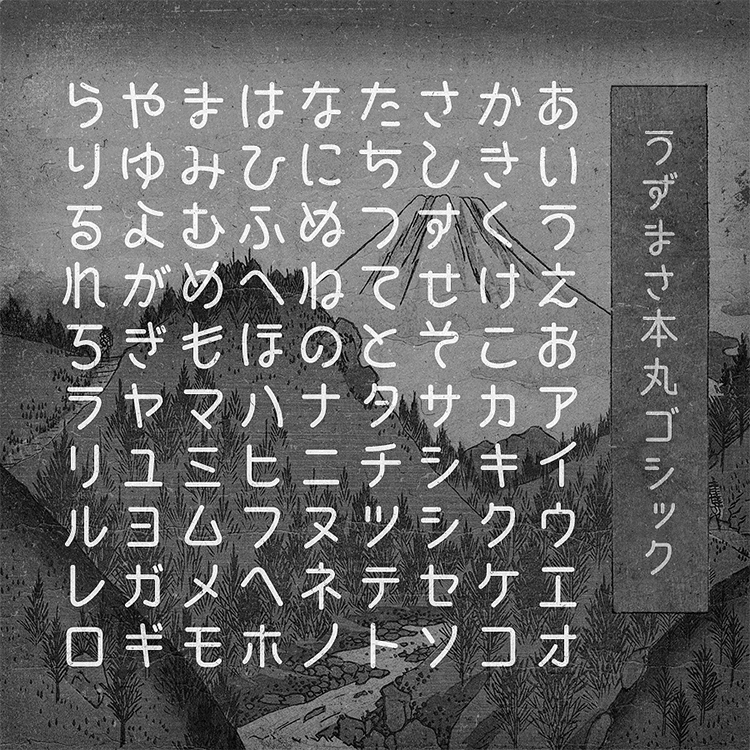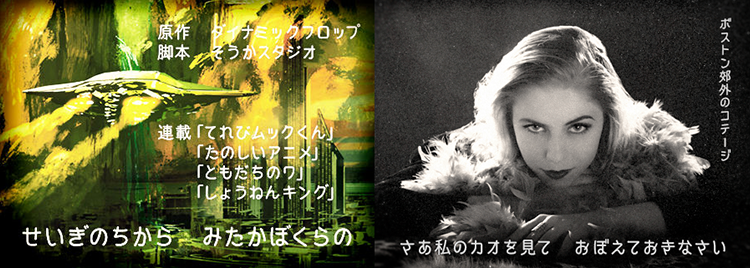
うずまさ本丸ゴシックは、無声映画時代(戦前1920年代)の字幕文字をヒントに、現代に蘇らせたフォントです。京都市右京区太秦(うずまさ)をイメージした、丸ゴシック体のフォントになっています。暖かみのある字体が特徴で、YouTubeやニコニコ動画などの字幕から、ロゴや雑誌などの紙媒体まで幅広く使うことができます。
字体は規則性があり、モダンな印象を与えます。和風なデザインから、現代的なやさしいデザイン、カワイイデザインまで幅広いデザインにマッチします。文字の重心が上にあり、アンバランスさがユーモラスな魅力につながっています。
うずまさ本丸ゴシックアニメ(左)、うずまさ本丸ゴシック-シネマ(右)の使用サンプル
フリーフォントの「うずまさ本丸ゴシックmini」と製品版の「うずまさ本丸ゴシック」があります。
製品版は、第一水準の漢字2965字と第二水準のよく使う漢字460字、記号類・約物・キリル文字・半角カタカナ等647字が含まれています。フリーフォントとは異なり、縦書きも可能になっています。また、TrueTypeも梱包されています。
製品版には特典として、4つの書体が入っています。「うずまさ本丸ゴシックアニメ」は古い昭和アニメのテロップ風の書体、「うずまさ本丸ゴシック-シネマ」は普通の字幕文字風の書体、「うずまさ本丸ゴシック-シネマ斜体」は縦に斜体の字幕文字の書体です。さらに、うずまさ本丸ゴシックの個性を少し減らして使いやすくなった「うずまさ本丸ゴシック-ノーマル」が入っています。